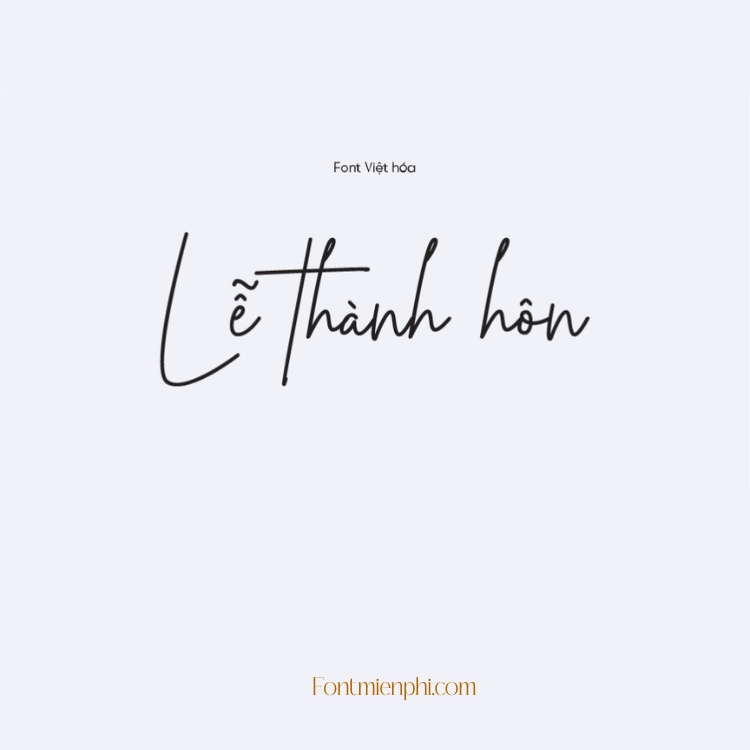
Font Việt hóa VIP South Australia
Giới thiệu về Font Việt hóa VIP South Australia
Trong thế giới thiết kế đồ họa hiện đại, việc tìm kiếm một bộ Font Miễn Phí chất lượng cao luôn là ưu tiên hàng đầu của các designer. Font Việt hóa VIP South Australia nổi lên như một lựa chọn hoàn hảo nhờ phong cách thanh lịch và phóng khoáng. Đây là một phông chữ thuộc dòng Script mang hơi hướng thủ công, giúp các tác phẩm trở nên gần gũi và đầy tính nghệ thuật. Được tinh chỉnh kỹ lưỡng để phù hợp với bảng mã tiếng Việt, bộ font này loại bỏ hoàn toàn lỗi hiển thị dấu, mang lại trải nghiệm mượt mà trên mọi phần mềm thiết kế.
Đặc điểm nổi bật của phông chữ
Font Việt hóa VIP South Australia sở hữu những đường nét uốn lượn tự nhiên nhưng vẫn giữ được sự rõ ràng, dễ đọc. Điều này khiến nó trở nên rất đa dụng trong nhiều ngữ cảnh khác nhau. Các nhà thiết kế thường sử dụng bộ font này cho các dự án yêu cầu sự tinh tế như thiệp cưới, bìa sách, hay các banner quảng cáo thời trang cao cấp. Sự kết hợp giữa nét thanh và nét đậm tạo nên một nhịp điệu thị giác ấn tượng, giúp thông điệp của bạn dễ dàng chạm đến cảm xúc của người xem.
Ứng dụng Font Việt hóa VIP South Australia trong thiết kế
Với vẻ ngoài sang trọng, Font Việt hóa VIP South Australia cực kỳ phù hợp cho việc xây dựng bộ nhận diện thương hiệu. Bạn có thể dùng nó để thiết kế logo cho các quán cà phê, spa hoặc shop hoa thủ công. Ngoài ra, phông chữ này còn phát huy thế mạnh trong việc tạo ra các câu trích dẫn (quotes) trên mạng xã hội, giúp bài đăng của bạn trở nên thu hút và chuyên nghiệp hơn. Khả năng tương thích tốt giúp người dùng dễ dàng cài đặt trên cả Windows và macOS.
Lưu ý khi sử dụng bộ font
Mặc dù Font Việt hóa VIP South Australia mang lại giá trị thẩm mỹ cao, người dùng cần lưu ý kết hợp nó với các font chữ không chân (Sans Serif) để tạo sự cân bằng cho bố cục. Việc sử dụng quá nhiều ký tự uốn lượn trong một đoạn văn dài có thể gây rối mắt, vì vậy hãy ưu tiên dùng bộ font này cho các tiêu đề hoặc các điểm nhấn quan trọng trong bản thiết kế của bạn.
Kết luận về bộ phông chữ South Australia